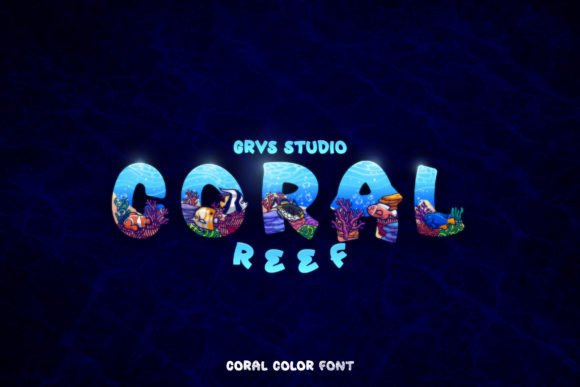
Grvs Coral Reef Colorful Decorative Svg
適切なデザイン要素を見つけるのは難しい場合がありますが、Grvs Coral Reef Colorful Decorative Svgは作品を即座に引き立てる優れたコレクションを提供します。
精密に作られたGrvs Coral Reef Colorful Decorative Svgは、クリーンなベクター、滑らかなタイポグラフィ、そして安心のための商用ライセンスを提供します。
POD(オンデマンド印刷)製品、結婚式の招待状、またはソーシャルメディアのグラフィックを作成している場合でも、Grvs Coral Reef Colorful Decorative Svgは理想的です。